Schriftsippe
»Schriftsippe« ist ein typografischer Terminus für eine Gruppe zusammengehöriger Schriftfamilien aus unterschiedlichen Schriftarten (Schriftuntergruppen), die typometrisch aus einer Grundschrift entwickelt wurden und deren Buchstaben, Ziffern und Sonderzeichen in der Regel die gleichen Grundformen und Proportionen besitzen, jedoch unterschiedliche Klassifikationsmerkmale aufweisen; Schriftgroßfamilie; Polyschriftsystem; eng. Superfamily.
Etymologisch von lt. »scriptum« zu »scribere« für dt. »Schreiben« bzw. »Schrift« und »Sippe« von mhd. »sippe« bzw. got. »sibja« für »Verwandtschaft« bzw. idg. »sebho« für »eigene Art«. Im Deutschen wurde »Sippe« im 18. Jh. insbesondere in der Wissenschaft im Sinne von »Verwandtschaftsverhältnis« wiederbelebt.
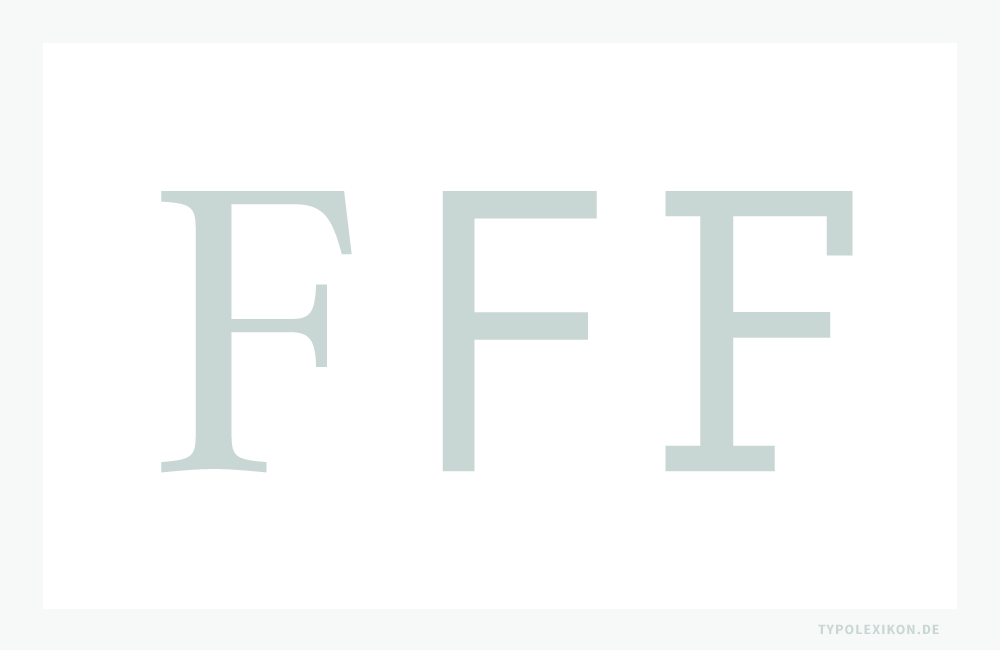
Schriftsippen umfassen in der Regel Schriftschnitte (Schriftstile) aus den Hauptschriftgruppen Antiqua, Grotesk und Egyptienne in jeweils unterschiedlichen Schriftbreiten (z.B. schmal oder breit), Schriftlagen (z.B. normal oder kursiv) und Schriftstärken (z.B. mager oder fett) – vereinzelt auch Antiqua Varianten (z.B. Zierschriften), dicktengleiche Schriften (z.B. Monospaced Fonts), spezielle Ziffernsätze (z.B. Tabellenziffern oder Kapitälchenziffern), musikalische oder wissenschaftliche Zeichensätze (z.B. mathematische Zeichen) und Nichtrömische Schriften (z.B. kyrillisch).
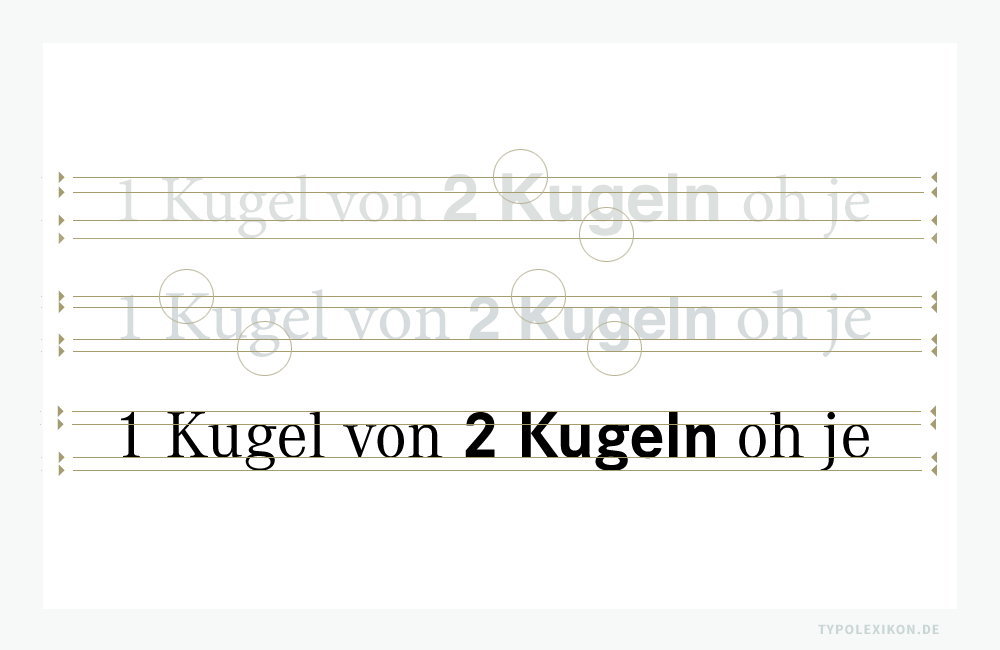
Vorteile von Schriftsippen
Schriftsippen, beispielsweise die Corporate A-S-E 1) oder die Compatil™,2) werden heute als Schriftsysteme verstanden, um effizient komplexe typografische Anforderungen im Corporate Publishing zu lösen.
- Schriftsippen sind in Ihrer Anwendung einfach zu handhaben. Mikrotypografisches Wissen ist – im Vergleich zur extrafamiliären Schriftmischung – kaum nötig.
- Schriftsippen verfügen in der Regel über viele unterschiedliche Schriftschnitte, die vom Schriftgestalter:in aufeinander abgestimmt sind. Sie eigenen sich deshalb besonders gut, um komplexe semantische Typologien in eine typografische Auszeichnungsmatrix umzusetzen (siehe Schriftmischung).
- Schriftsippen sparen bei extrafamilären Schriftauszeichnungen spürbar Zeit, da Oberlängen, Mittellängen und Unterlängen nicht angepasst werden müssen.
- Schriftsippen verfügen in allen Hauptschriftgruppen über die gleichen Hauptschriftlinien, weshalb Schriftmischungen auch bei lauten Auszeichungen harmonisch wirken.
- Schriftsippen verfügen oft über einen außergewöhnlichen großen Zeichenvorrat. Sie eigenen sich deshalb oft auch als Expertensätze, um komplexe Medien zu setzen, beispielsweise Geschäftsberichte, wissenschaftliche Bücher oder Zeitungen.
- Schriftsippen verfügen oft über dicktengleiche Formvarianten, Tabellenziffern und Nichtrömische Alphabete, was eine »Corporate Typography« vereinfacht.
- Dicktenkompatible Schriftsippen sind im Gemischten Satz und bei Animationen in Websites (z.B. Hover-Effekte) empfehlenswert, da alle ihre Figuren schnell austauschbar sind, ohne dass sich dabei die Satzbreite oder der Umbruch ändert. Ebenso können im Nachhinein laute und leise Schriftauszeichnungen vorgenommen werden, was bei der Umsetzung einer semantisch-typografischen Auszeichnungsmatrix sehr hilfreich ist.
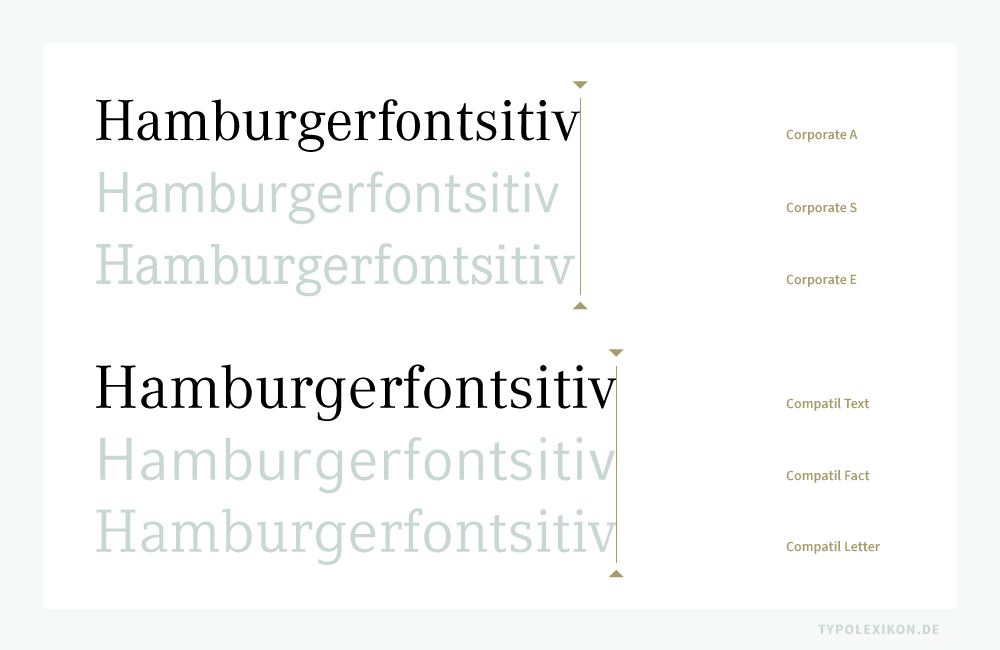
Vertreter von Schriftsippen
Dual-, Trilogie- und Polyschriftsysteme
| Schriftsippe | Schriftgestalter/in | Font Foundry | Jahr |
|---|---|---|---|
| Arccus | Heitmann, Hans R. | Finaltype | 2020 |
| Authentic | Huschka, Karin | Linotype | 1999 |
| Compatil® | Bilz, Silja Faulhaber, Erik Haus, Reinhard Leu, Olaf | Linotype | 2001 |
| Corporate A-S-E | Weidemann, Kurt | URW | 1990 |
| Foundry | Quay, David Sack, Freda | Linotype | 1989 |
| Guardian | Barnes, Paul Schwartz, Christian | Commercial Type | 2005 |
| Komplex | Heitmann, Hans R. | Finaltype | 2020 |
| Legst | Heitmann, Hans R. | Finaltype | 2021 |
| Lucida | Bigelow, Charles Holmes, Chris | Lucida® Fonts | 1984 |
| Meta | Spiekermann, Erik | FontFont | 1991–2010 |
| Nexus | Majoor, Martin | FontFont | 2004 |
| Officina ITC | Chaeva, Isabella Schäfer, Ole Spiekermann, Erik van Rossum, Just | Adobe Elsner+Flake ITC ParaType | 1990 |
| Quadraat | Smeijers, Fred | FontFont | 1992 |
| Rotis | Aicher, Otl | Agfa Linotype | 1989 |
| Scala | Majoor, Martin | FontFont | 1990–1993 |
| Stone | Stone, Summer | ITC | 1987–2010 |
| Syntax | Meier, Hans Eduard | Linotype Stempel | 1968–1995 |
| Thesis | de Groot, Lucas | LucasFonts | 1994–2000 |
Bezugsquellen von Schriftsippen
Schriftsippen werden von Font Foundries als Kollektionen, in Schriftfamilien und in Form von einzelnen Schriftschnitten in unterschiedlichen Font Technologien (z.B. TTF, OTF, Webfonts) angeboten (siehe auch Schriftwahl). 3)
| ↑1 | Anmerkung: Die Corporate A-S-E wurde Ende der 1980er Jahre im Auftrag der Daimler Benz AG (E. Reuter, Mercedes) von Kurt Weidemann (1922–2011) entworfen, von Kurt Stecker gezeichnet, von Günter Gerhard Lange (1921–2008) in der Protovariante »gefinisht« und von URW digitalisiert. |
| ↑2 | Anmerkung: Das Schriftsystem Compatil® wurde unter der Regie von Olaf Leu von Silja Bilz, Erik Faulhaber und Reinhard Haus für die Linotype GmbH entworfen. |